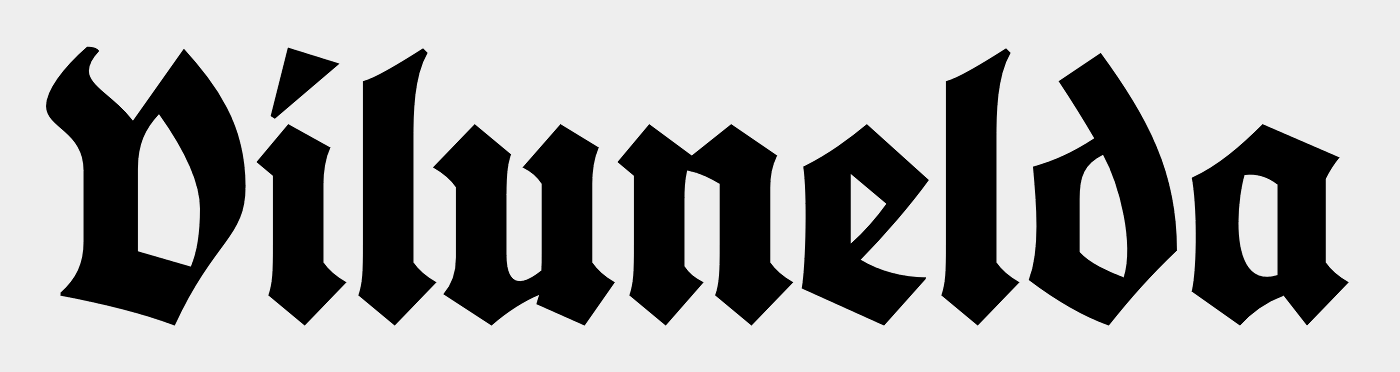
Historische Schriften von Häusern gesucht
zu folgenden Hauswandschriften suche ich möglichst ähnliche digitale Varianten.
Da kommen sicher von den Foren-Goten noch besser Vorschläge … :-)
Foren-Goten
Ungekoppelt wäre das ein prima Kniffelkandidat gewesen: Forengoten. Was musst du auch immer so kundenfreundlich sein! :nana:
Oder,  hat mein kein Programm das sie von J. Mach Wust einprogrammierten Smartfont-Techniken unterstütz, dann bei mir mit Ligaturen im PUA:
oder, auch bei mir in gleicher Codierung: Dieter Steffmanns Variante:
Der zweie Text "Gasthof Mühle" stammt eindeutig vom örtlichen Maler, der mit Schrift wohl ein wenig auf Kriegsfuß stand, und eben mal was hin gepinselt hat.
Ach übrigens: bei mir auf Usedom gibt es einen Ort "Gothen", und die waren wohl einst hier auch daheim.